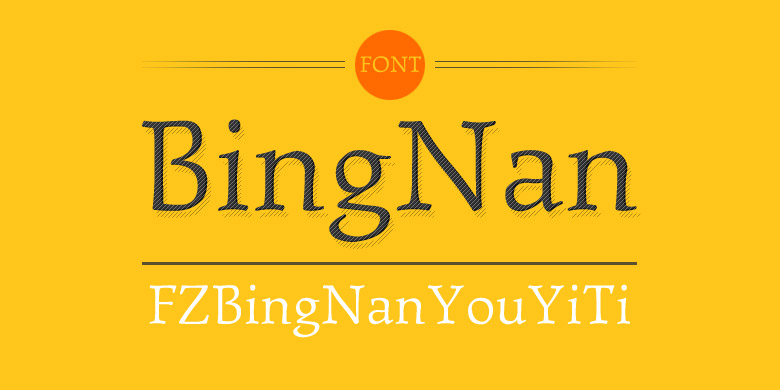
方正秉楠友谊体
方正秉楠友谊体,这款字体结构工整、笔画清晰,兼顾美观与易读性,适用于标题、正文、海报、包装、LOGO 等多种场景。字形优雅稳定,风格百搭耐看,适配日常排版与创意设计,让文字呈现更舒适、更具质感。方正秉楠友谊体一笔一画,皆是细节,以均衡的比例、流畅的线条打造舒适视觉体验,字形端正大气,风格简约现代。无论是商业设计、品牌宣传还是日常排版,都能轻松驾驭,让文字更有格调与力量。方正秉楠友谊体字体下载。
字体品牌: 方正字库 方正字库 设计师:余秉楠 字体分类:衬线体 字体属性:精品字 字符集:Unicode 发布时间: 2012